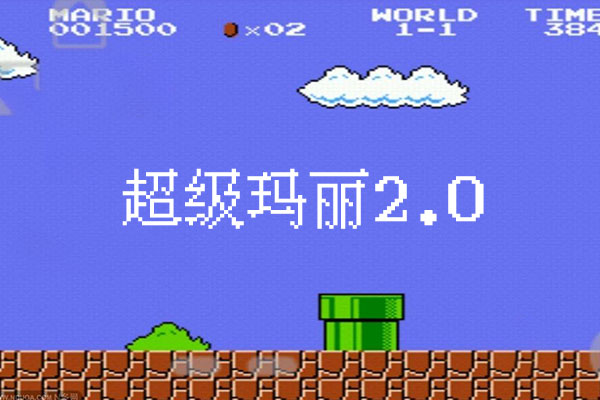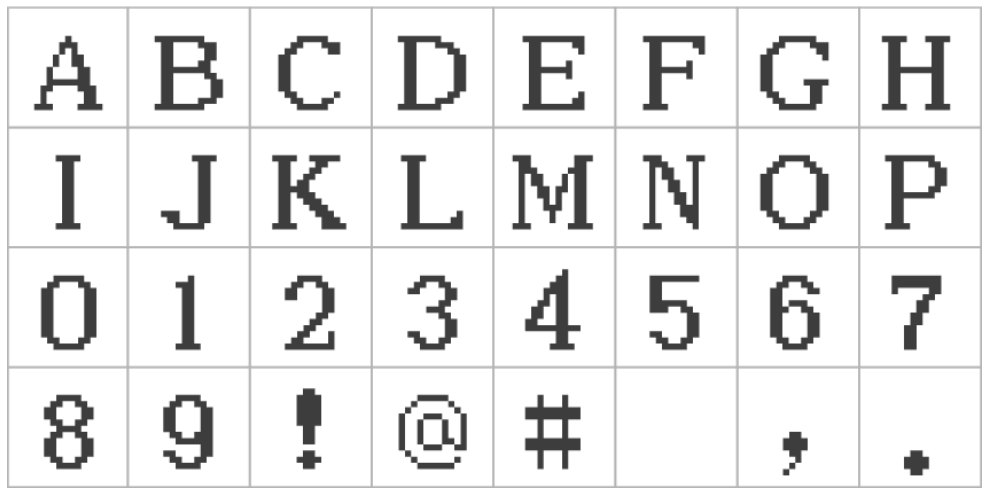
IPix中文像素字体
中文像素字体(IPix / Chinese Pixel Font)是一款具有特色的字体,它是一种像素风格的中文字体,包含了超过6000个常用汉字,让人回想起80年代红白游戏机的经典时代。这款字体是通过使用HZK16字模制作而成的,呈现出独特的复古风格,非常适合在游戏中使用,尤其是复古风格的游戏项目。
这款中文像素字体不仅适合于商业用途,而且可以用于游戏等娱乐领域。其独特的像素风格将为你的设计带来别具一格的视觉效果,使你的作品更加具有吸引力和创新性。无论是用于制作游戏、设计海报,还是进行其他类型的创意设计,中文像素字体都比较合适。